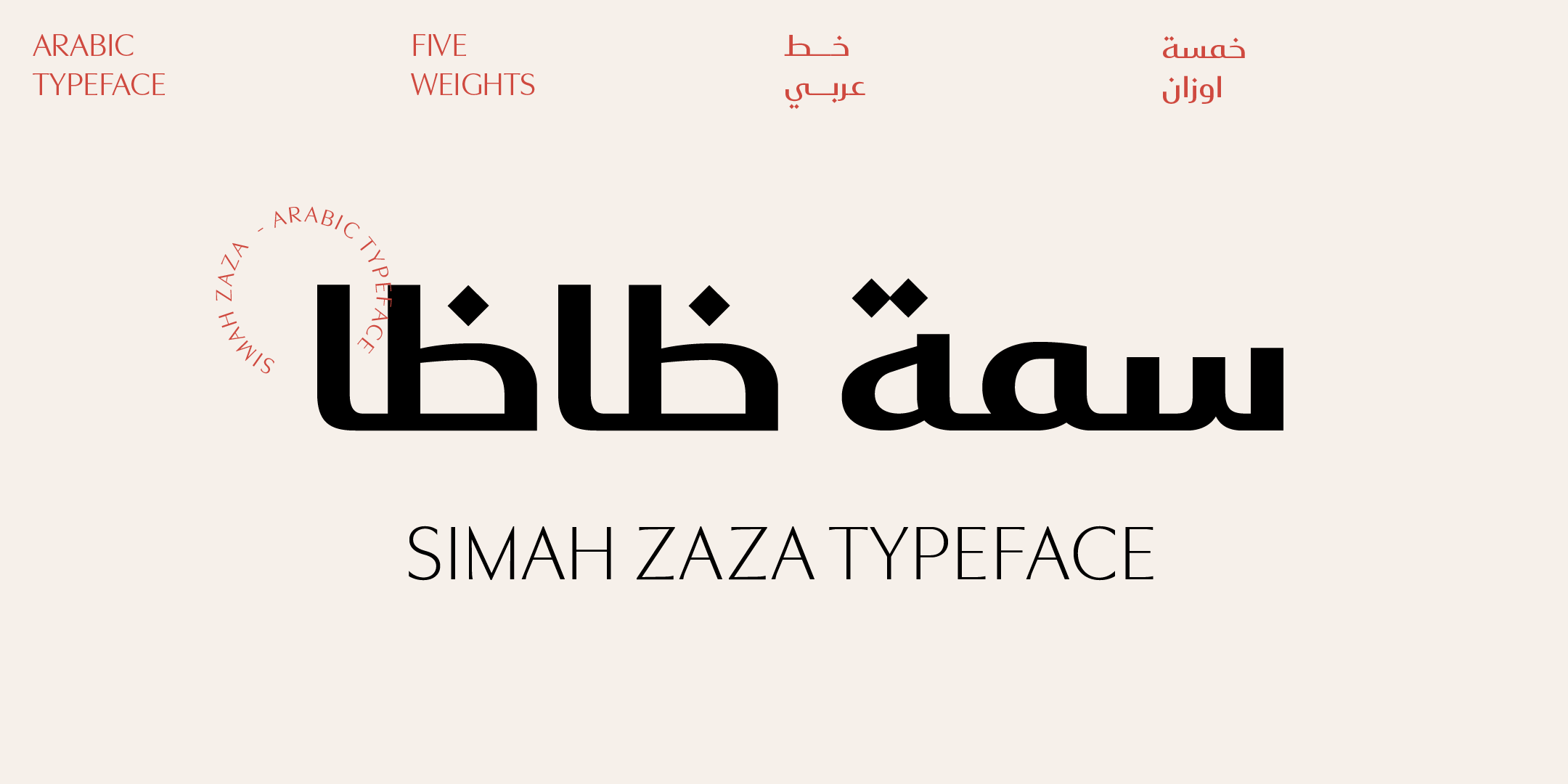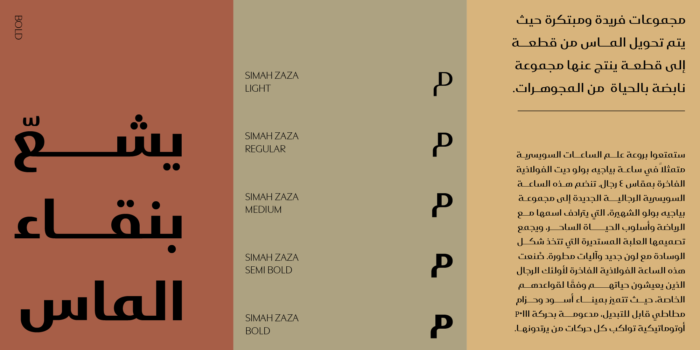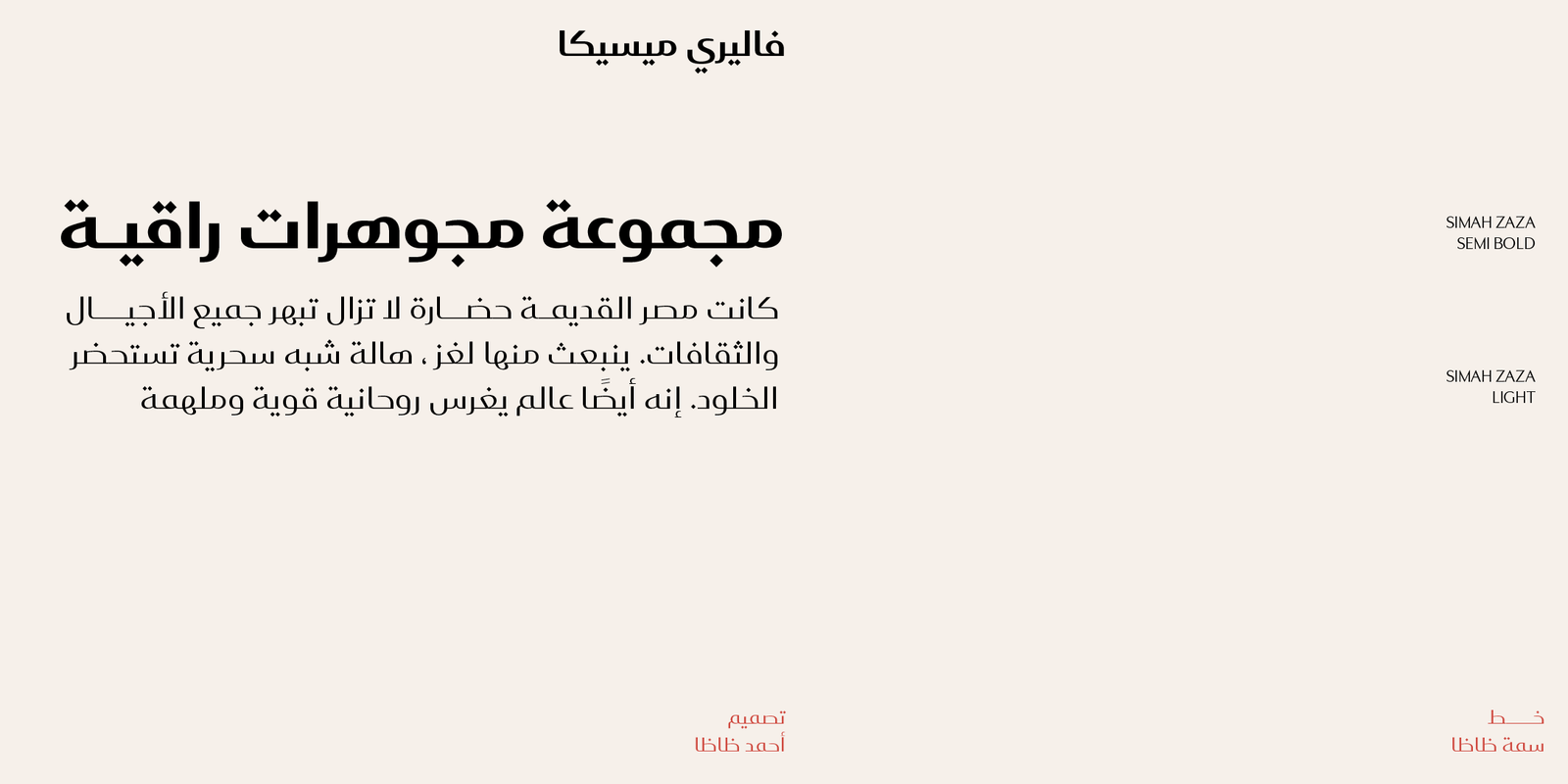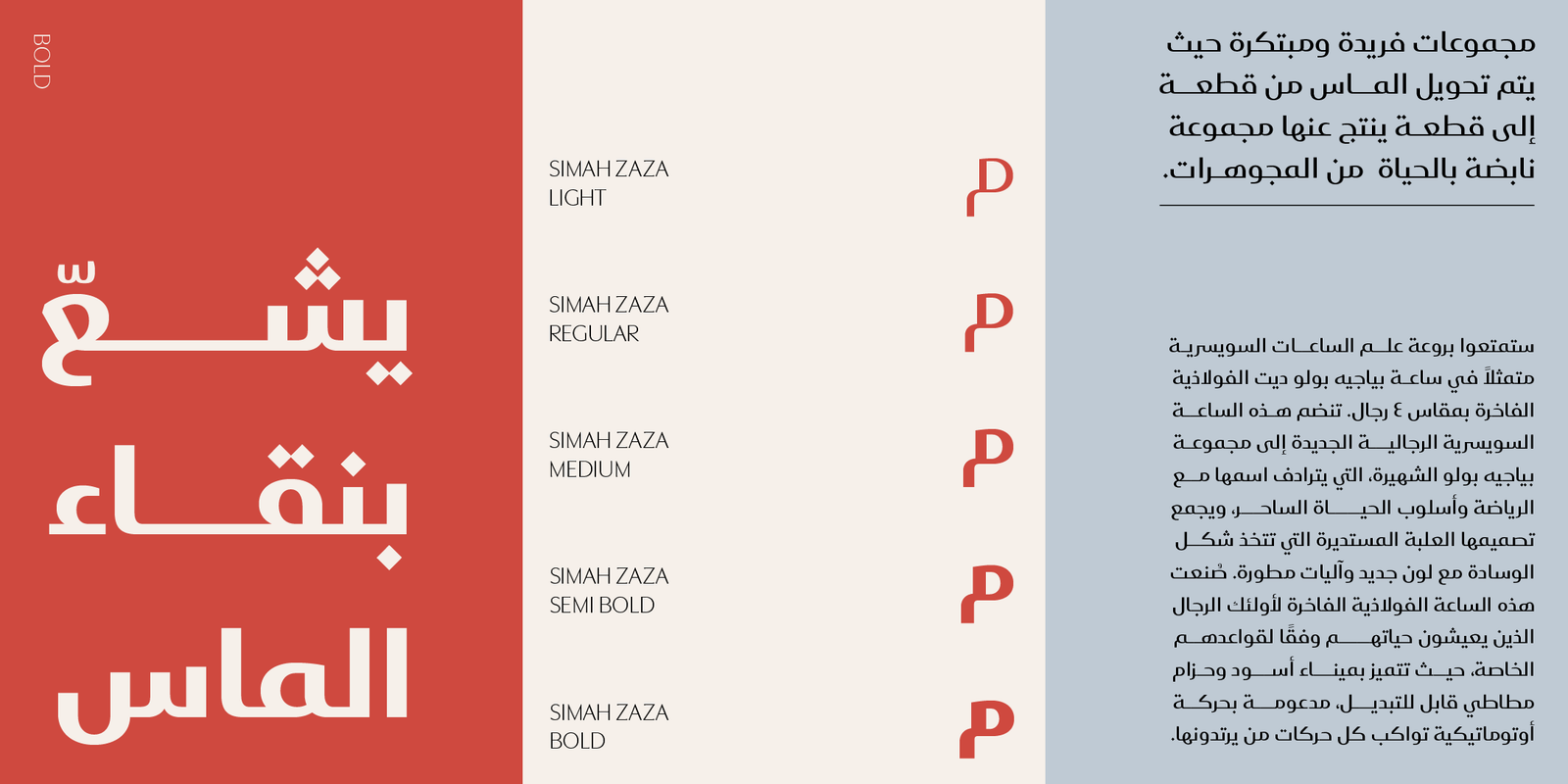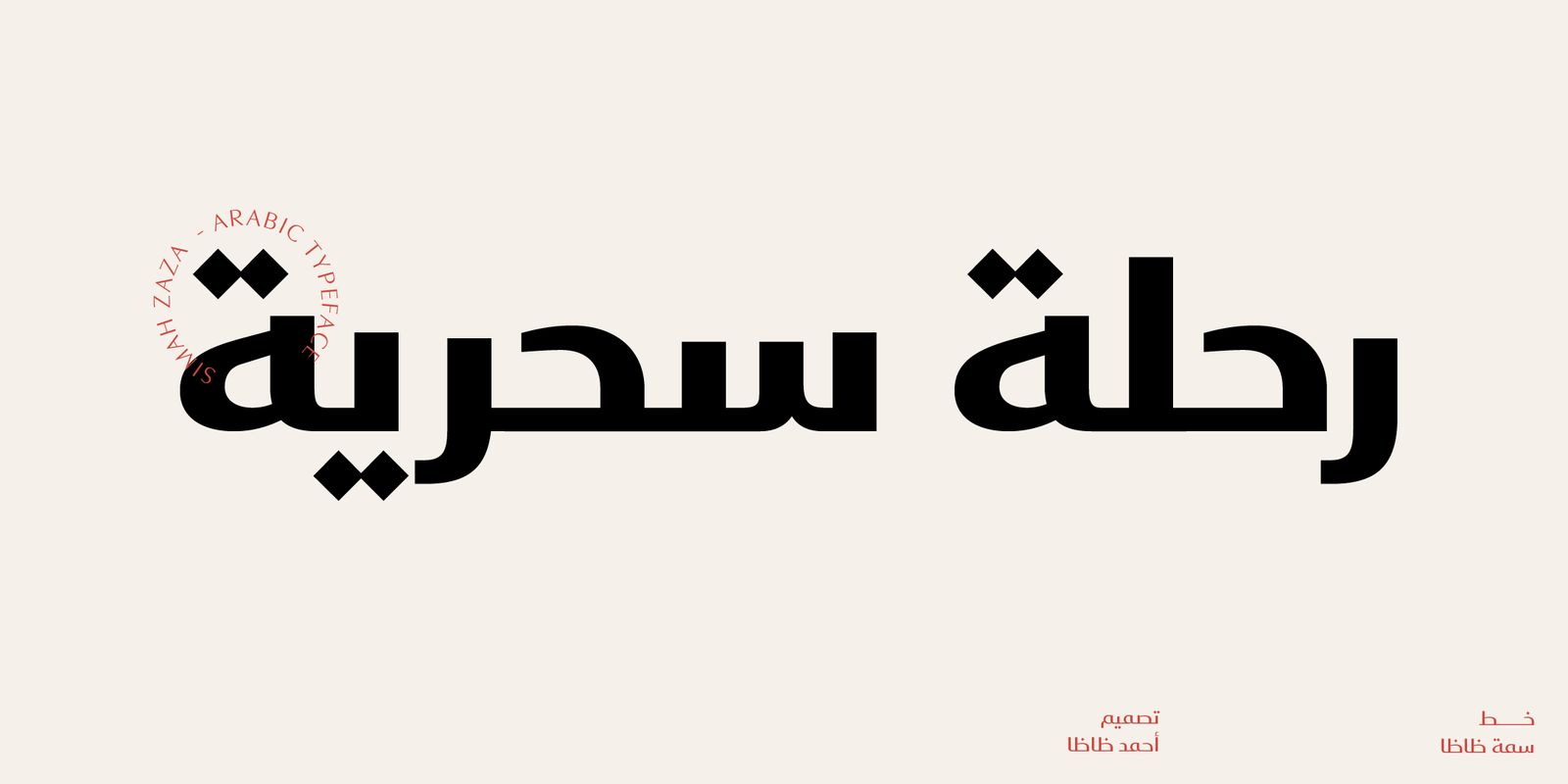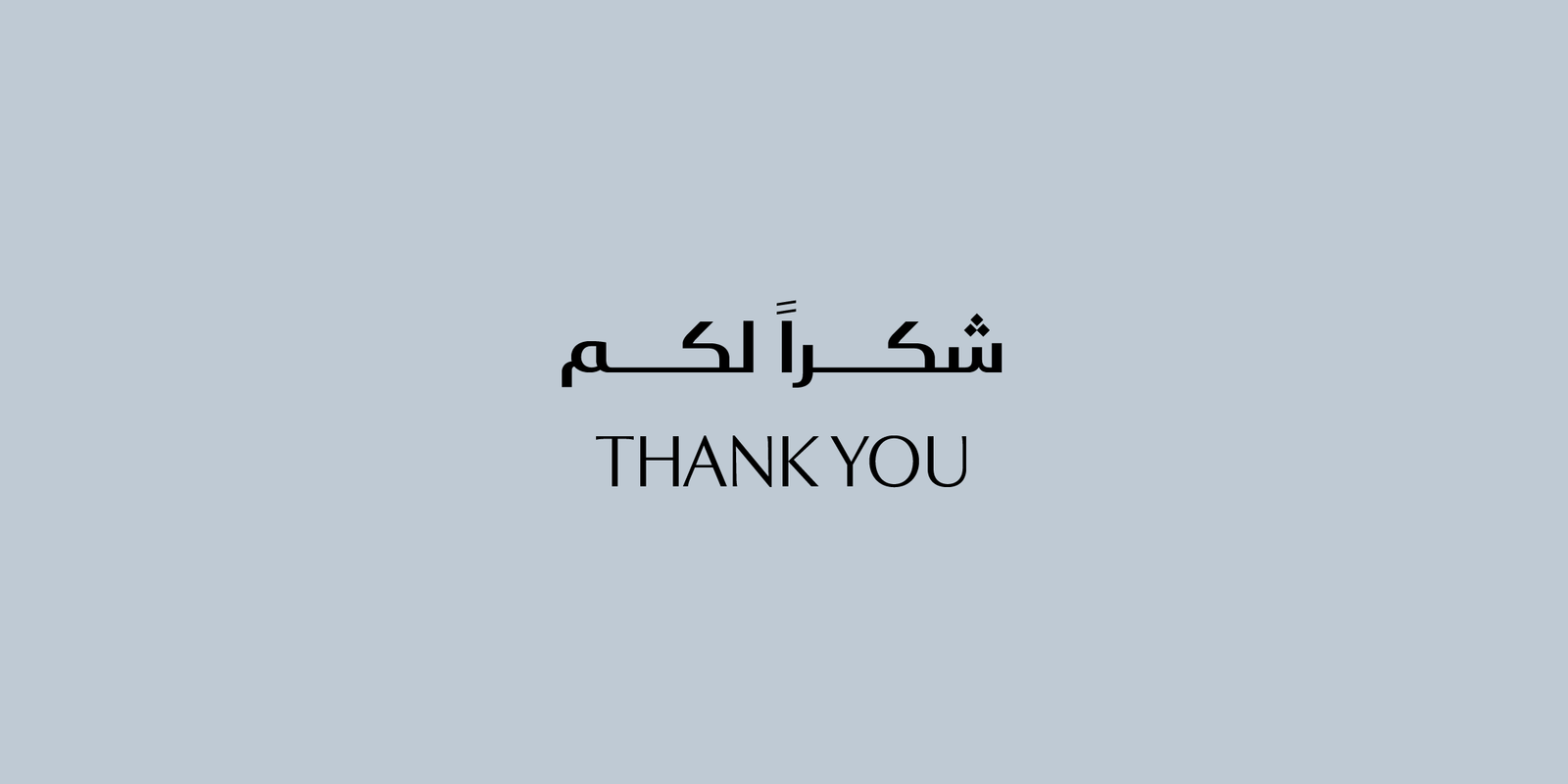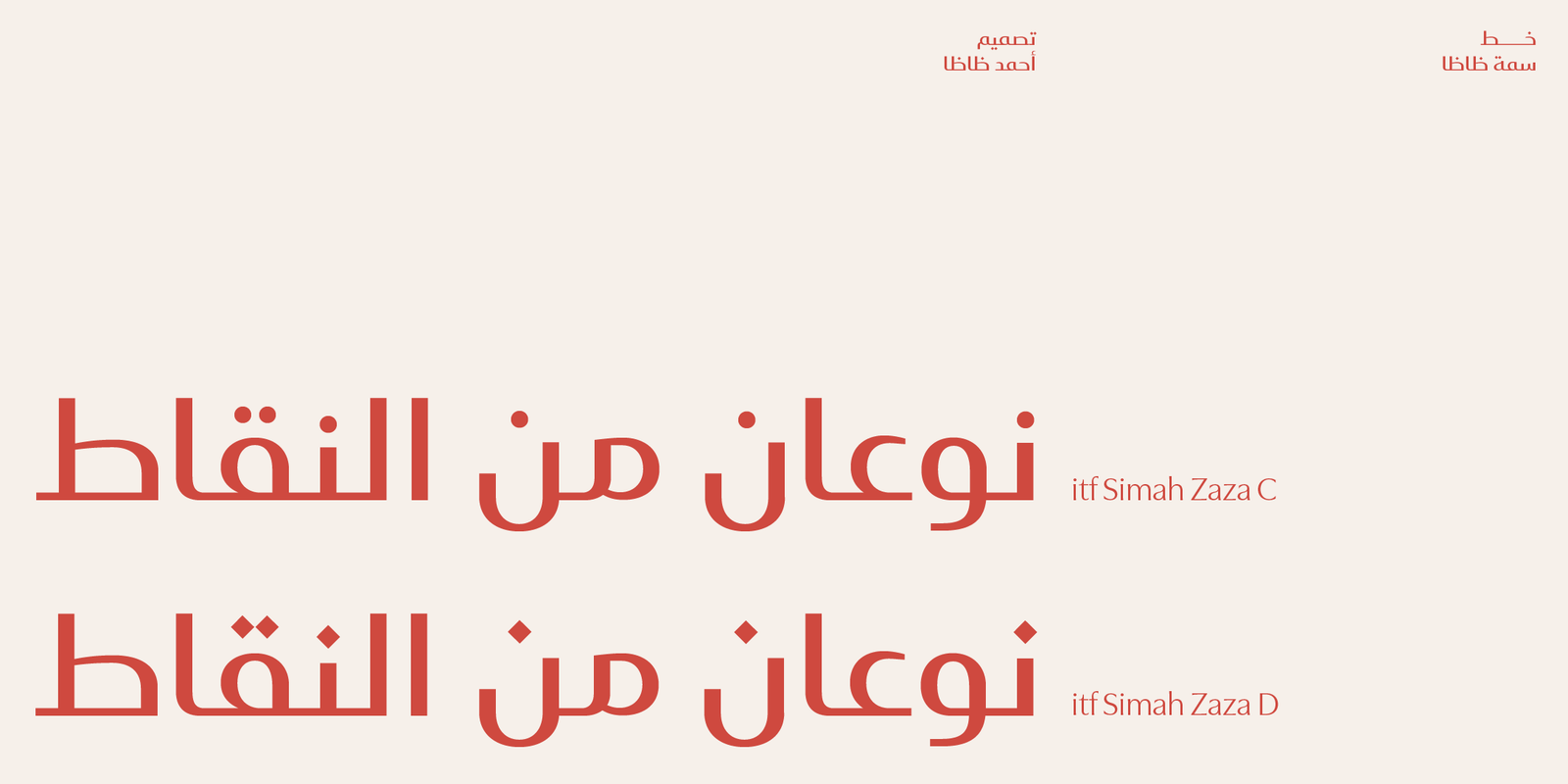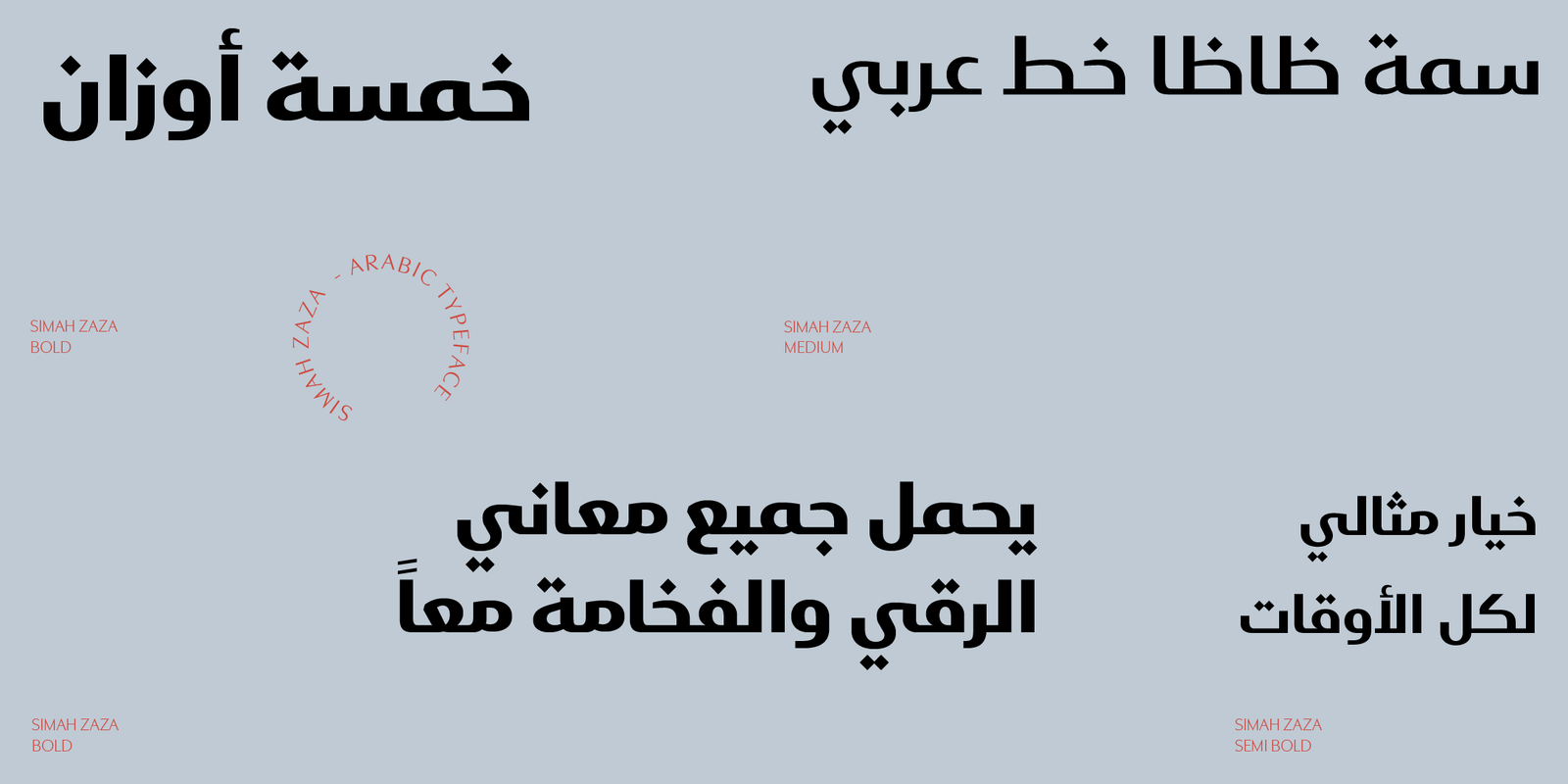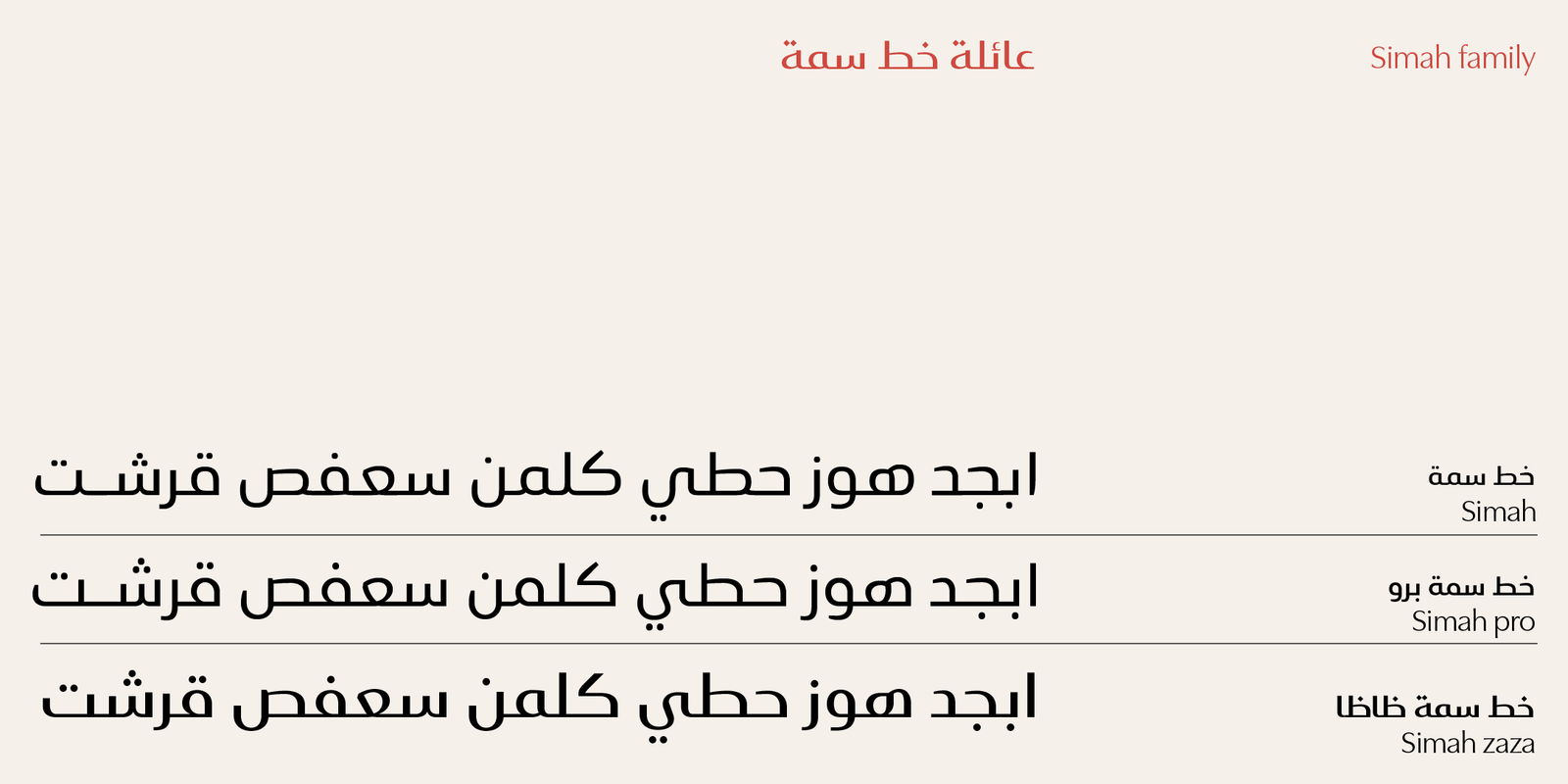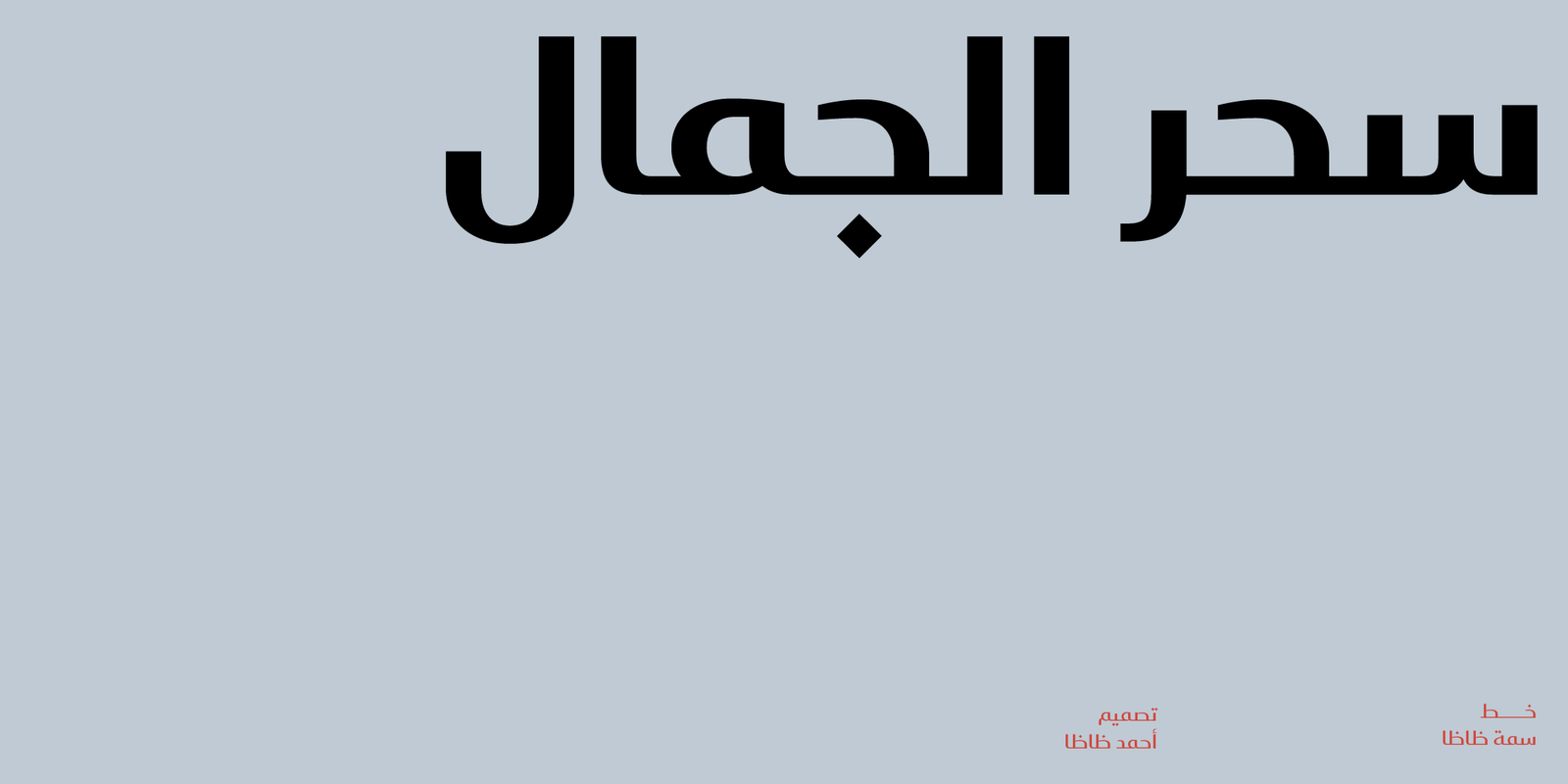
Simah zaza arabic typeface – خط سمة ظاظا العربي
Simah zaza typeface – خط سمة ظاظا العربي
خط سمة ظاظا هو خط عربي يجمع بين الفخامة والدفء مع لمسة إنسانية فريدة، مما يجعله خيارًا مثاليًا لتصميم طباعي عربي حديث وخطوط عربية معاصرة. يتميز الخط بالوضوح والمرونة والبساطة، مما يجعله معاصرًا ومناسبًا للاستخدامات المتنوعة. مستوحى من الخط الكوفي ومُتأثر بأسلوب النسخ، تم تصميم سمة ظاظا بعناية فائقة لضمان أدائه الممتاز سواء على الشاشات أو في الطباعة.
- خمسة أوزان: يتوفر الخط بخمسة أوزان تتراوح بين الخفيف والعريض لتلبية احتياجات التصميم المختلفة.
اللغات: العربية فقط، بلا حروف لاتينية